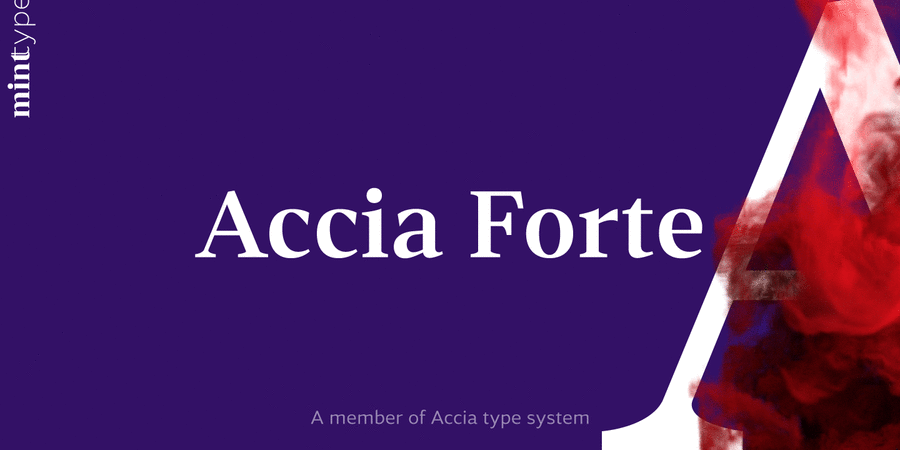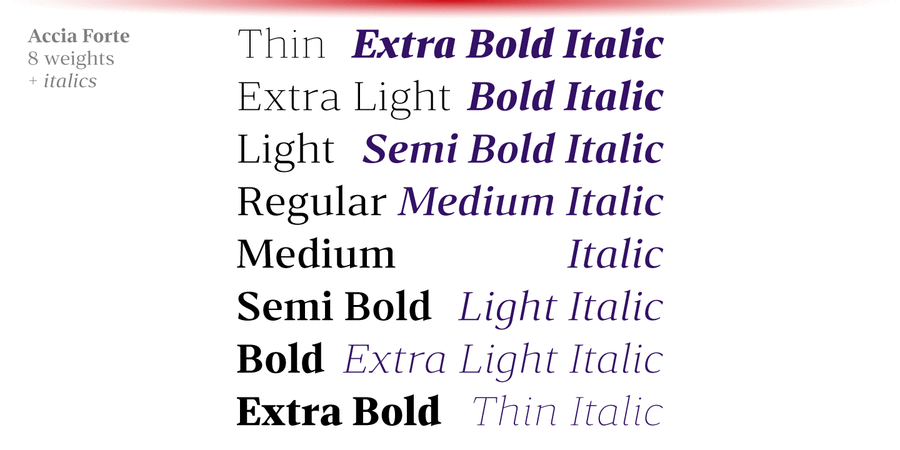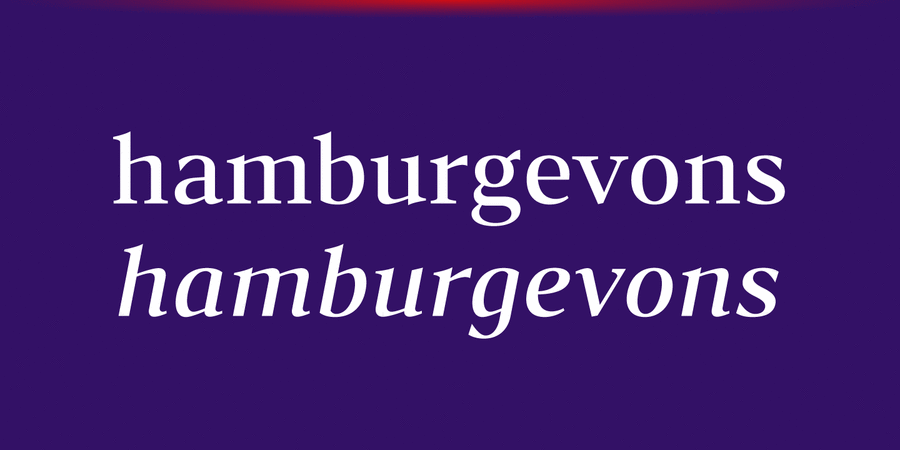
Опис гарнітури Accia Forte – це сильна контрастна антиква з великою висотою рядкових і помітними зарубками. Його гучне сучасне звучання ідеально підійде для заголовків на обкладинках, постерах і веб-сторінках. Шрифтове сімейство містить 8 накреслень від Thin до Extra Bold з відповідними курсивами. Кожне накреслення має велику мовну підтримку, включно з кирилицею, а також численні функції OpenType: капітель, лігатури, кілька наборів цифр, пунктуація з урахуванням регістру, дроби й індекси. Accia Forte є частиною супергарнітури Accia, куди входять п'ять шрифтів, від гротеску до виразної антикви. Це дає вам можливість проектувати максимально складні серії продукції або інформаційні системи. Система Accia складається з Accia Sans, Accia Flare, Accia Piano, Accia Moderato і Accia Forte. Гарнітуру розробив Андрій Константинов в студії Mint Type у 2021 році.
Особливості сімейства шрифтів Accia ForteХіт десятиліття:
Хіт 2010-х Схожий на шрифти з логотипів, ігор, фільмів:
Forbes, Oxford, The Guardian
Асоціації з сімейством шрифтів Accia ForteОсобистість і характер гарнітури:
тонкий, худий, витончений, делікатний, легкий, модний, якісний, культурний, добірний, благородний, гармонійний, елітний, дорогий, красивий, майстерний, знаменитий, оригінальний, багатий, міський, прозорий, гострий, колючий, розкішний, художній, рівний, космополітичний, технічний, сучасний, точний, логічний, освічений, серйозний, розумний, твердий, чіткий, різкий, динамічний, комільфо, діловий, формальний, виразний, характерний, аристократичний, історичний, світський, цікавий, стійкий, пафосний, імперський, яскравий, гордий, переконливий, авторитетний, дзвінкий, сильний, помітний, урочистий, амбітний, римський, владний, видовищний, грандіозний, великий, величний, монументальний, впевнений, претензійний, значний, мотивуючий, відповідальний
срібло, мода, музика, ресторан, розкіш, комільфо, Місто, люкс, годинник, бутік, література, культура, філософія, преміум, готель, шоколад, сервіровка, опера, театр, музей, історія, мистецтво, золото, костюм, краватка, проза, юрист, адвокат, фінанси, правосуддя, економіка, карти, чай, банкнота, кава, Трофей, нагорода, гроші, детектив, бібліотека, суд, влада, вечір, імператор, взуття Гарнітура асоціюється з віком: